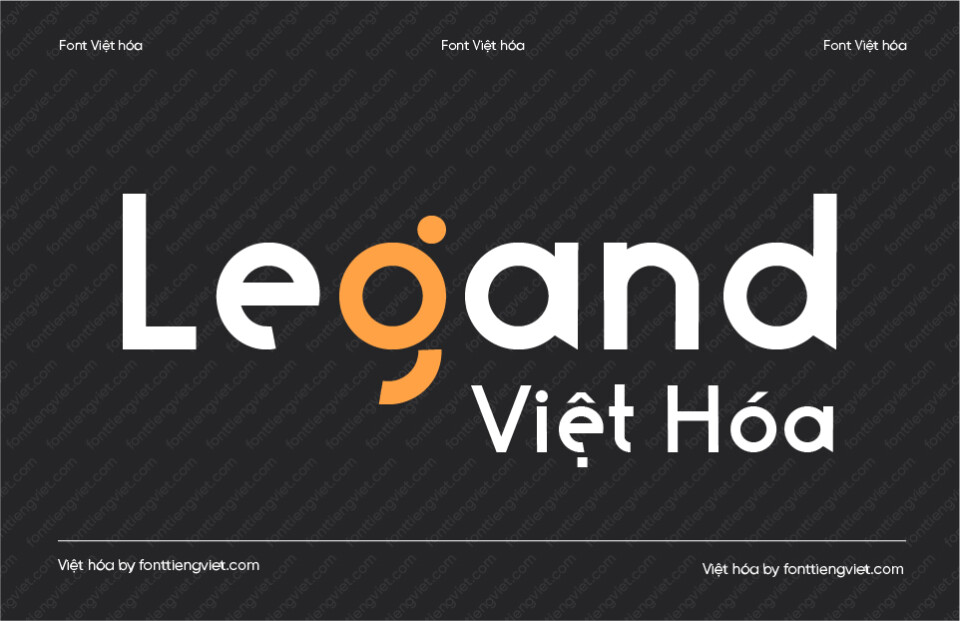
Font Việt hóa 1FTV VIP Legand
Font Việt hóa 1FTV VIP Legand: Bộ font chữ sang trọng và đẳng cấp cho thiết kế chuyên nghiệp
Giới thiệu về Font Việt hóa 1FTV VIP Legand trong thiết kế đồ họa
Trong thế giới sáng tạo, việc lựa chọn một Font Miễn Phí chất lượng luôn là ưu tiên hàng đầu của các nhà thiết kế. Font Việt hóa 1FTV VIP Legand nổi lên như một hiện tượng nhờ sự kết hợp hoàn hảo giữa nét cổ điển và hơi thở hiện đại. Đây là bộ font được tinh chỉnh kỹ lưỡng về dấu tiếng Việt, giúp người dùng không còn lo lắng về lỗi hiển thị khi soạn thảo nội dung. Với những đường nét thanh mảnh nhưng vô cùng dứt khoát, bộ font này mang đến một cảm quan về sự sang trọng, quyền lực và không kém phần tinh tế. Đối với các bạn học sinh hay thầy cô giáo, việc sử dụng font chữ này sẽ giúp các bài thuyết trình hoặc tài liệu học tập trở nên cuốn hút và chuyên nghiệp hơn hẳn so với những phông chữ mặc định thông thường trên máy tính.
Những đặc điểm nổi bật của Font Việt hóa 1FTV VIP Legand
Khả năng hiển thị tối ưu và linh hoạt
Font Việt hóa 1FTV VIP Legand sở hữu bảng mã ký tự đa dạng, hỗ trợ đầy đủ các ký tự đặc biệt trong tiếng Việt. Điểm mạnh lớn nhất của bộ font này chính là sự cân bằng giữa các khoảng cách chữ (kerning), giúp văn bản luôn dễ đọc dù ở kích thước lớn hay nhỏ. Các nét chữ được thiết kế với độ dày vừa phải, tạo cảm giác thanh thoát nhưng vẫn đủ mạnh mẽ để làm tiêu đề cho các ấn phẩm truyền thông. Ngoài ra, tính tương thích của font trên các phần mềm thiết kế phổ biến như Adobe Photoshop, Illustrator hay các ứng dụng văn phòng như Word và PowerPoint là cực kỳ ấn tượng, đảm bảo quy trình làm việc luôn mượt mà.
Văn phong thiết kế sang trọng và chuyên nghiệp
Đúng như tên gọi “VIP Legand”, bộ font này mang trong mình một khí chất huyền thoại và cao cấp. Các đường cong của chữ cái được vuốt ve tỉ mỉ, tạo nên sự mềm mại nhưng vẫn giữ được cấu trúc hình học chuẩn mực. Khi ứng dụng Font Việt hóa 1FTV VIP Legand vào các sản phẩm như thiệp mời, bìa sách giáo khoa hay các chứng nhận khen thưởng trong nhà trường, nó sẽ ngay lập tức nâng tầm giá trị thẩm mỹ của tác phẩm. Đây không chỉ đơn thuần là một công cụ viết chữ, mà còn là một phương tiện truyền tải cảm xúc và phong cách cá nhân của người sáng tạo.
Ứng dụng thực tế của Font Việt hóa 1FTV VIP Legand
Sử dụng trong giáo dục và trình chiếu
Trong môi trường học đường, Font Việt hóa 1FTV VIP Legand có thể được sử dụng để thiết kế các banner chào mừng, tiêu đề bài giảng điện tử hoặc các tờ rơi sự kiện trường học. Với phong cách rõ ràng, học sinh sẽ dễ dàng tiếp nhận thông tin hơn. Thầy cô có thể dùng font chữ này để tạo điểm nhấn cho những nội dung quan trọng, giúp bài giảng thêm sinh động và chuyên nghiệp. Sự chỉn chu trong việc chọn font chữ cũng là cách để giáo dục các em về tư duy thẩm mỹ và sự tôn trọng đối với người xem ngay từ những điều nhỏ nhất.
Thiết kế thương hiệu và ấn phẩm cá nhân
Không chỉ dừng lại ở giáo dục, Font Việt hóa 1FTV VIP Legand còn là lựa chọn lý tưởng cho việc thiết kế logo, bộ nhận diện thương hiệu cá nhân hoặc các bài đăng trên mạng xã hội. Nếu bạn đang tìm kiếm một phông chữ có khả năng gây ấn tượng mạnh mẽ ngay từ cái nhìn đầu tiên, thì đây chính là giải pháp hoàn hảo. Sự độc đáo của nó giúp sản phẩm của bạn tách biệt hoàn toàn với đám đông, tạo nên một dấu ấn riêng biệt và đẳng cấp mà khó có bộ font nào cùng phân khúc có thể làm được.
Kết luận về bộ Font Việt hóa 1FTV VIP Legand
Tóm lại, Font Việt hóa 1FTV VIP Legand là một tài nguyên quý giá cho bất kỳ ai đang theo đuổi con đường thiết kế hoặc đơn giản là muốn làm mới những trang văn bản của mình. Với sự kết hợp giữa tính thẩm mỹ cao và khả năng ứng dụng thực tế tuyệt vời, bộ font này xứng đáng có một vị trí trong thư viện font chữ của bạn. Việc sử dụng những Font Miễn Phí, Font Việt Hóa, Font Việt hóa 1FTV VIP Legand không chỉ giúp tiết kiệm chi phí mà còn đảm bảo nội dung tiếng Việt luôn đẹp mắt và chuẩn xác. Hãy thử trải nghiệm và cảm nhận sự khác biệt mà bộ font đẳng cấp này mang lại cho các dự án sáng tạo sắp tới của bạn.